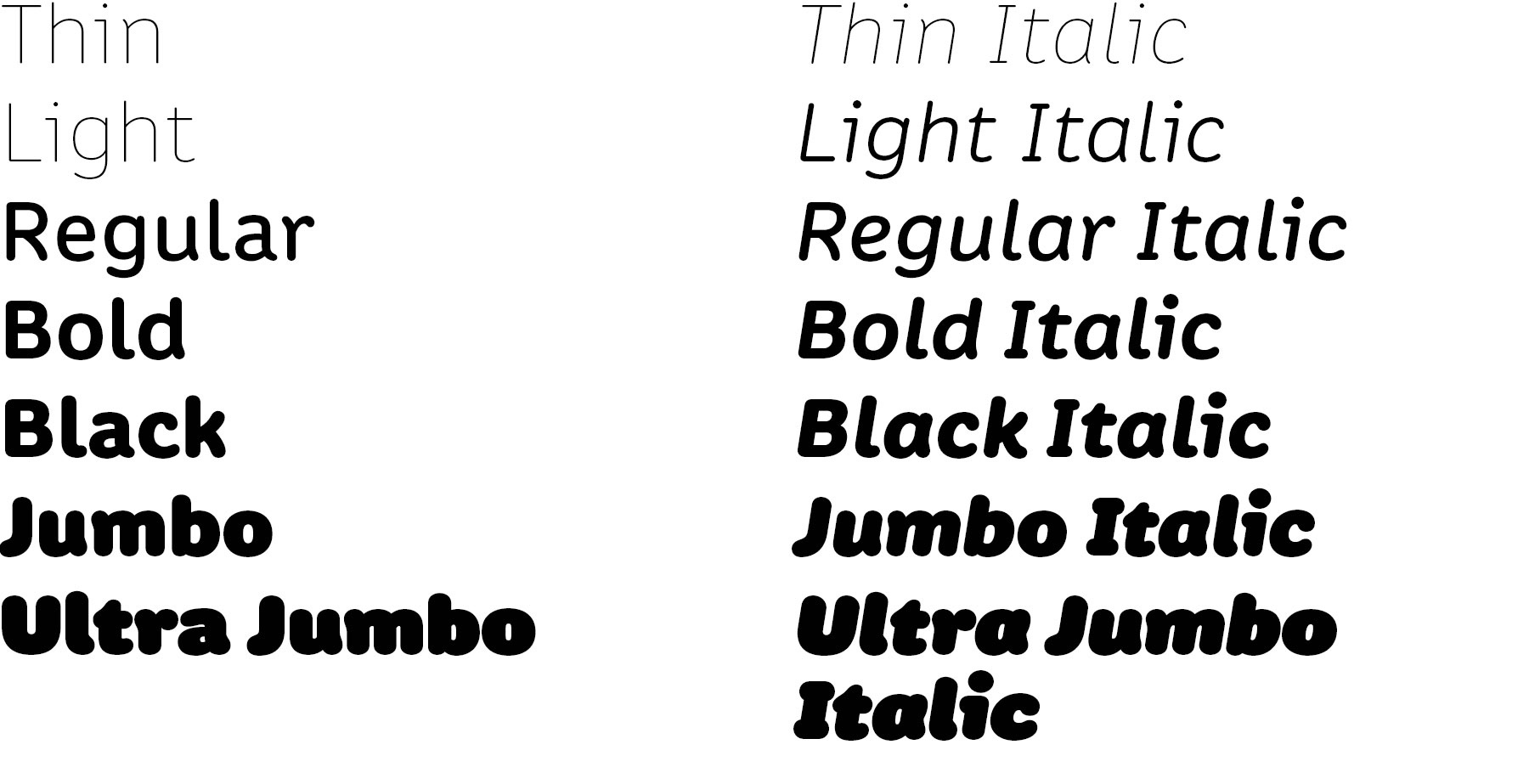
Fotobuch Schwangerschaft
ich erstelle gerade in Indesign ein Fotobuch zum Thema Schwangerschaft. Die Bilder (viele sind s/w) möchte ich mit Überschriften und kleinen Texten versehen. Kennt jemand von Euch eine schöne Schrift die passen könnte.
Was macht denn für Dich eine Schwangerschaft aus? Welche Empfindungen, Eindrücke soll die Schrift transportieren?
Für den Anfang kann ich mir die Canape oder die Vulpa vorstellen.
Vielen Dank! Die Vulpa Italic gefällt mir!
Das Buch zeigt wie der Bauch stetig wächst und die Vorfreude der Eltern...
Die Schrift sollte angelehnt an den runden Bauch etwas geschwungen sein und Freude vermitteln.
Ich finde das Thema Schriften echt schwierig es gibt einfach so viele und man wird schier erschlagen. Vielen Dank für deinen Tipp
Mein spontaner Gedanke: Colette
As much as it is warm and friendly, Colette is structured. Designed by Greg Lindy to be suitable for a wide range of applications, Colette is elegant and reserved in its lighter weights and more boisterous in its heavier. Originally inspired by the birth of Greg’s daughter, Colette was actually developed as the typographic component for a capital campaign for a regional children’s hospital. Since the campaign’s completion, Colette has undergone refinements that include the addition of weights, italics and an extensive character set to support an array of latin-based languages.
Sowas in der Art hatte ich auch gedacht, hatte nur keine passende Schrift parat :gimmifive:
Mein spontaner Gedanke: Colette
Und die Schriftschnitte werden mit zunehmender Schwangerschaft immer fetter.
Je nach dem wie ernst oder lustig das Ganze wirken soll und auch wie lang die Texte sind kommen unterschiedliche Schriften in Frage. Für längere Texte würde ich etwas in Richtung Dolly oder Rooney empfehlen. Gibt es nur kurze Zitate kann es auch ein handgeschriebene Schrift wie die Liebe Gerda sein. Colette oder Marigny wäre wieder ein anderer Style. Je nach Art der Bilder kann ich mir da einiges vorstellen ...
Mir ist bisher nicht so richtig klar geworden, ob es um Schwangerschaften generell geht – oder eher um die Dokumentation einer konkreten Schwangerschaft. In letzterem Fall sollte man vielleicht eine Schriftwahl treffen, sie sich auch noch für die Dokumentation der Eskapaden von Baby und Kind eignet.
Ich weiß, ich weiß, so eine Schwangerschaft ist furchtbar spannend. Aber nur bis zur Geburt. Dann interessiert sich wirklich niemand mehr für Fotos von Ultraschalls und runden Bäuchen. Dann wollen alle nur noch Babygeschichten und -bilder.
Als »Hausschrift fürs Kind« fände ich die bereits empfohlene Canapé auch klasse. Freundlich und warm (ohne abgenudelt und kitschig zu sein) und sogar prima geeignet für das Lernen der Buchstaben in ein paar Jahren.
Einen Moment lang hatte ich Angst du willst auch hier wieder die Tannenberg vorschlagen :shock:
Hehe! Und ich wundere mich, dass hier noch keine Schriftnamen fielen wie Syntax, Avenir, Frutiger oder Arno. :-o
Syntax, Avenir, Frutiger oder Arno.
Das schien mir zu naheliegend, als dass ich es erwähnen müsste :hammer:
Ne, das mit dem Einscannen finde ich gut :nicken: